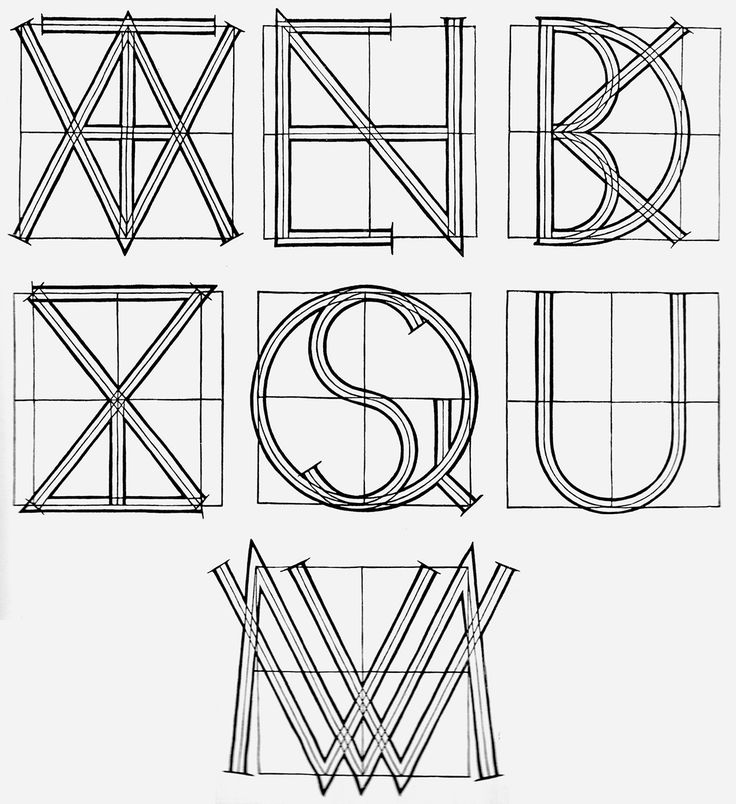
Построение шрифта Дюрера // Писаревский Д. А. Шрифты и их построение. Л., 1927.
Шрифту посвящен небольшой отрывок из третьей книги «Наставления к измерению циркулем и линейкой линий, плоскостей и объемных тел, составленного Альбрехтом Дюрером и напечатанного, с относящимися к сему рисунками, на пользу всем любителям искусства в 1525 году» («Underweysung der Messung, mit dem Zirckel und Richtscheyt, in Linien, Ebenen unnd gantzen corporen…»). Книга целиком на русский язык не переводилась. Отрывок о шрифте выходил в трех редакциях (четырех изданиях):
ПОСТРОЕНИЕ ШРИФТА ДЮРЕРА
(перевод с немецкого А. Н. Фоминой *).
Часто приходится делать шрифт на столбах, башнях и высоких стенах, поэтому, кто хочет писать на башне так, чтобы верхнюю строчку букв можно было бы прочесть так же легко, как и нижнюю, тот должен сделать ее наверху крупнее, чем внизу, следующим образом: поставь свое лицо на таком расстоянии от башни и на такой высоте, как ты хочешь.
к точке c и отрежь их до пересечения с вертикальной fg. Таким образом f, g будет разделена пропорционально делению на ab, которой она параллельна.
При увеличении надписи вертикаль помещается впереди a b, а при уменьшении — позади.
Такие деления применяются не только для написания букв, но и в других случаях. Этот способ пригоден, когда хотят украсить высокую башню во всех этажах изображениями так, чтобы верхние казались одинаковыми с нижними.
Так как строители и художники обычно делают надписи на высоких стенах, то необходимо, чтобы они научились правильно строить буквы; поэтому я хочу дать основные правила начертания латинского алфавита.
Прежде всего сделай квадрат для каждой буквы, в котором эта буква будет заключена. Когда ты вписываешь туда букву, делай толстую стойку буквы шириною в десятую часть стороны квадрата, а более тонкую стойку делай шириною в одну треть толстой.
Это имей в виду во всех буквах всей азбуки.
Сначала делай букву А так: обозначь углы ее квадрата a, b, c, d и делай это для всех букв. Раздели этот квадрат двумя пересекающимися линиями, вертикальной
Таким образом, в середине получается треугольник. Точка e приходится наверху в середине буквы. Потом соедини букву A под горизонтальной чертой gh. Делай эту перекладину шириной в одну треть широкой стойки. Затем начерти на верхней стороне квадрата циркулем окружность так, чтобы она касалась широкой стойки буквы
Делай это, чертя окружности, радиус которых должен равняться седьмой части стороны квадрата. Внутренний же выступ сделай в две трети ширины толстой стойки. Для этого с обеих сторон очерти дугу радиусом равным половине толстой стойки. Это A поверху ты можешь также плоско
[ 54 ]
обрезать по линии прямоугольника и закруглить букву спереди, как внизу. В этом случае линии наверху должны быть сдвинуты немного ближе. Обрати внимание на то, что, закругляя
Для буквы B сделай квадрат и раздели его горизонтальной линией e, f на две части.
Тогда начерти полуокружность, которая касалась бы этой линии, точки n и верхней горизонтальной линии аб. Проведи через точку n вертикальную линию, которая касалась бы внутренней стороны нижнего закругления и наружной стороны верхнего закругления. После этого тяни горизонтальную линию по Рис. № 13.
[ 55 ]
В букве B остаются три угла. В нижнем углу начерти выемку при помощи окружности, радиус которой равен
Наружные закругления вверху и внизу на прямой стойке буквы делай при помощи окружности, радиус которой равен ширине стойки.
Или делай В так: раздели сторону квадрата AC на девять частей и отдели верхние четыре части горизонтальной линией ef. Затем проведи вертикальную линию, как описано было ранее, но верхнее закругление делай между ef и cd.
Тогда раздели ab на девять частей и отрежь четыре части от b и обозначь это точкой g. Затем раздели